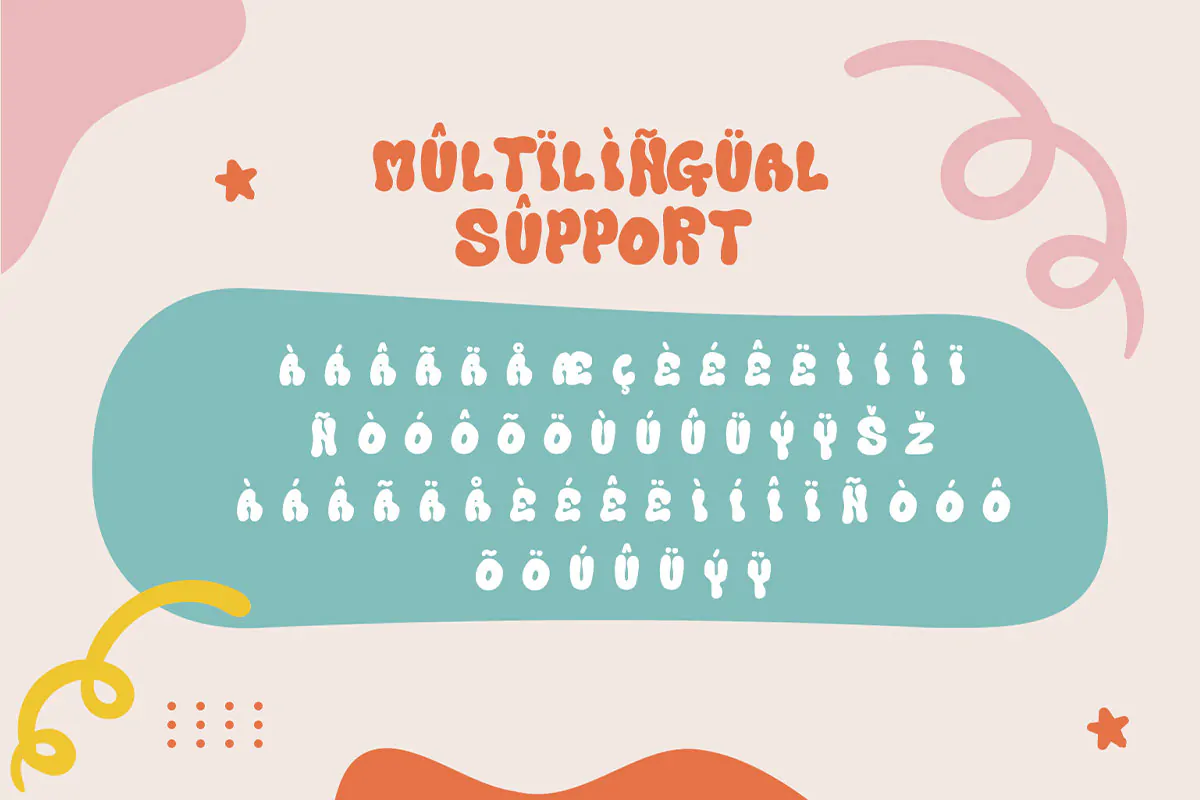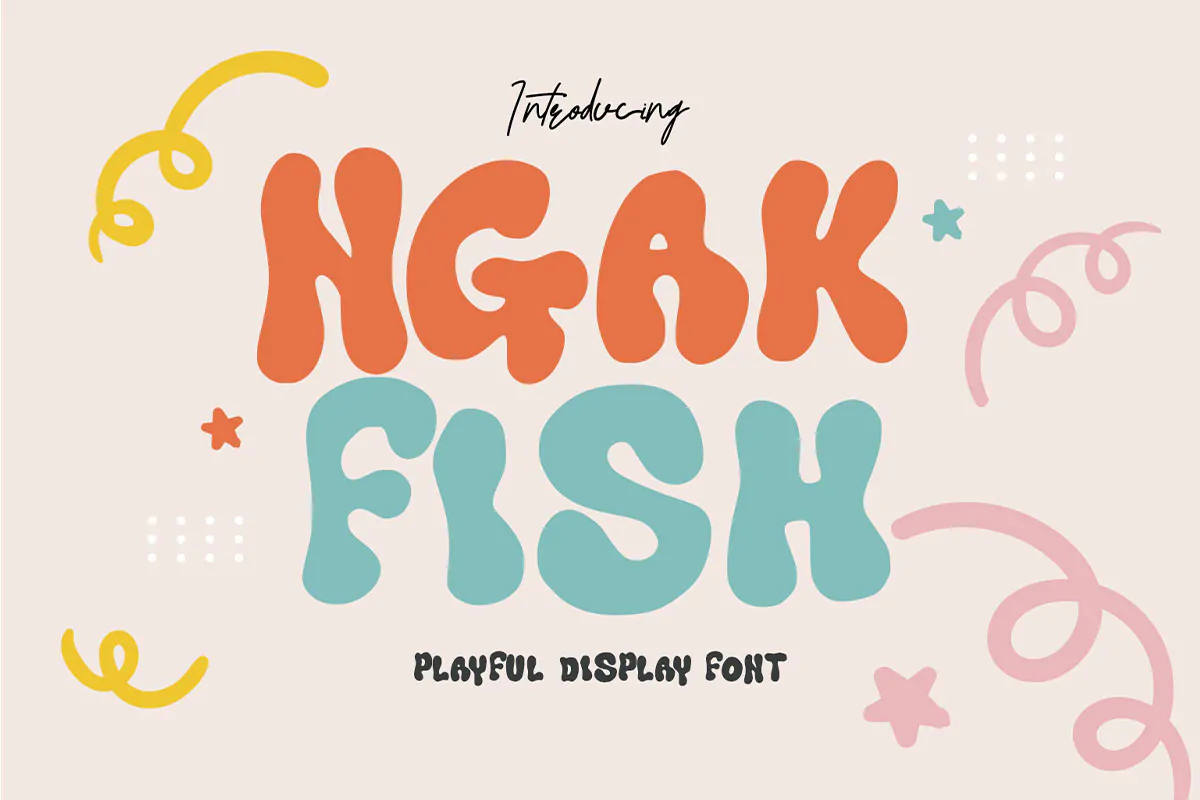
فونت کودکانه Ngak Fish
فونت کودکانه
فونت کودکانه Ngak Fish یک قلم انگلیسی زیبا است که به صورت دستنویس طراحی شده است و مناسب برای استفاده در پروژههای مختلف میباشد.
برای تایپوگرافی، پوستر، هویت بصری و محتوای چاپی یا دیجیتال قابل استفاده است.